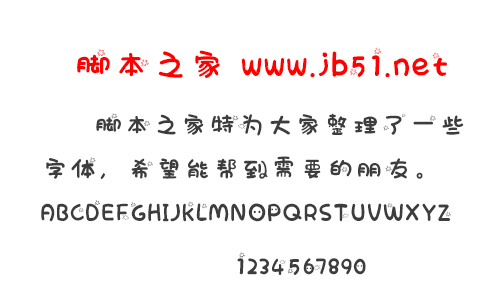
財運亨通小福豬是一款即個性又可愛的藝術(shù)字體,風(fēng)格比一般的字體更有特色,連貫字跡顯得干練而不凌亂,清新簡明,具有很好的視覺感,適合應(yīng)用于藝術(shù)設(shè)計、平面宣傳設(shè)計、網(wǎng)頁設(shè)計,書法字帖等領(lǐng)域,歡迎喜歡財運亨通小福豬字體的朋友前來下載使用。